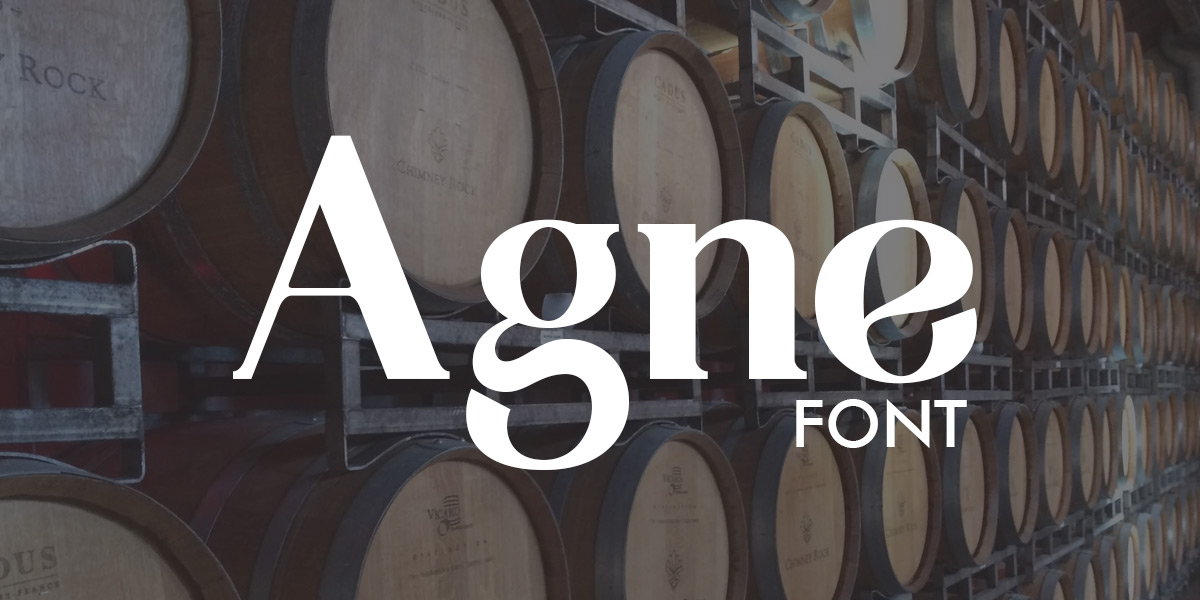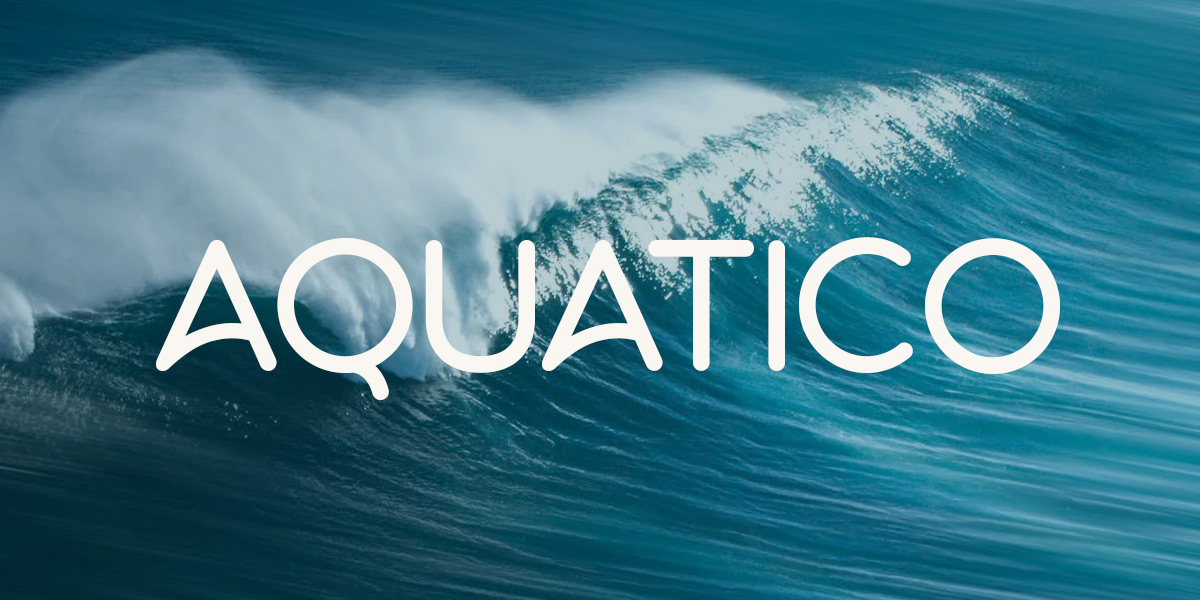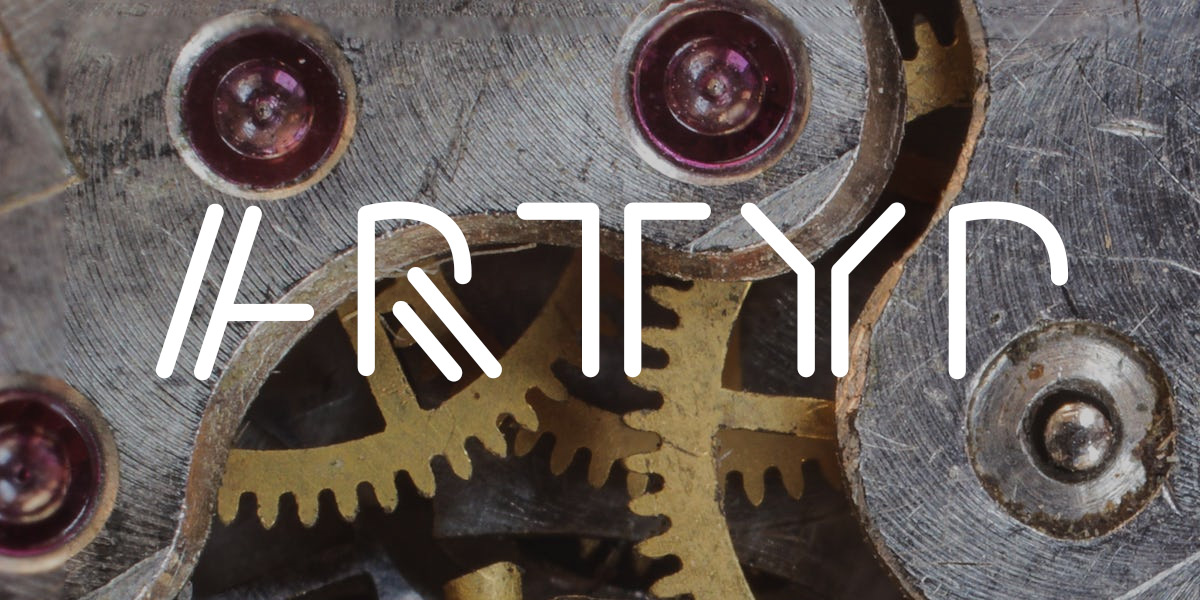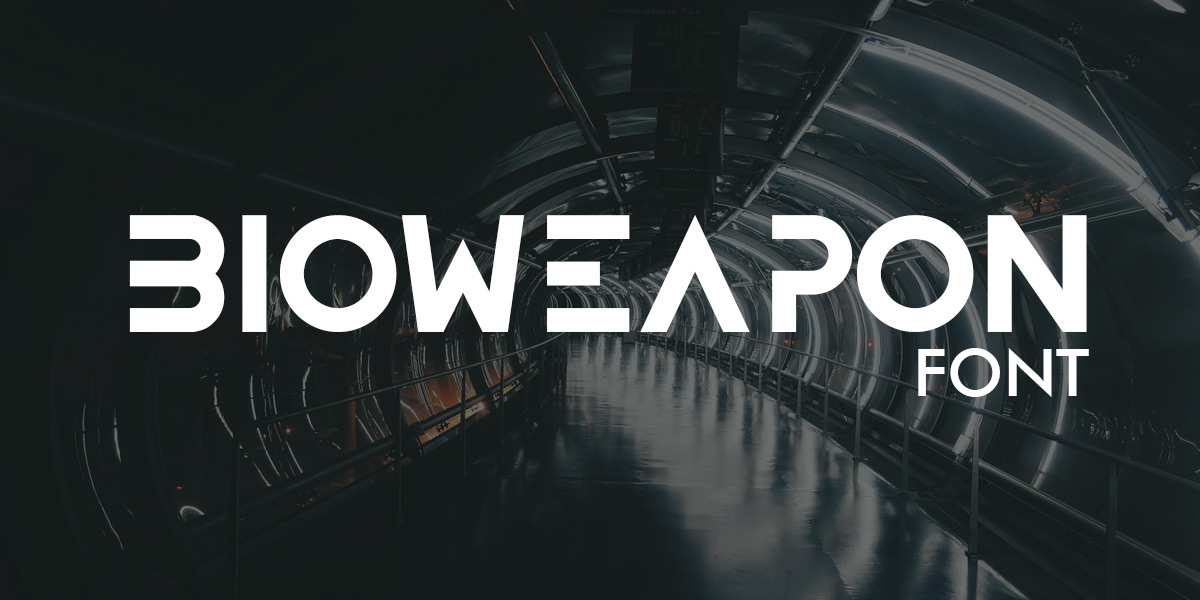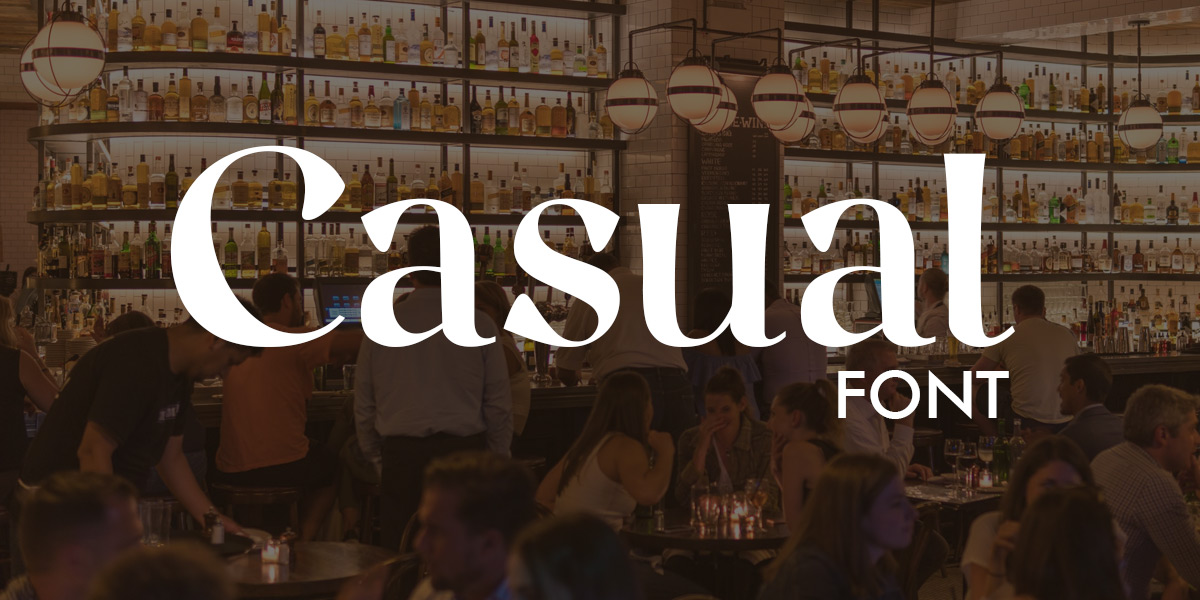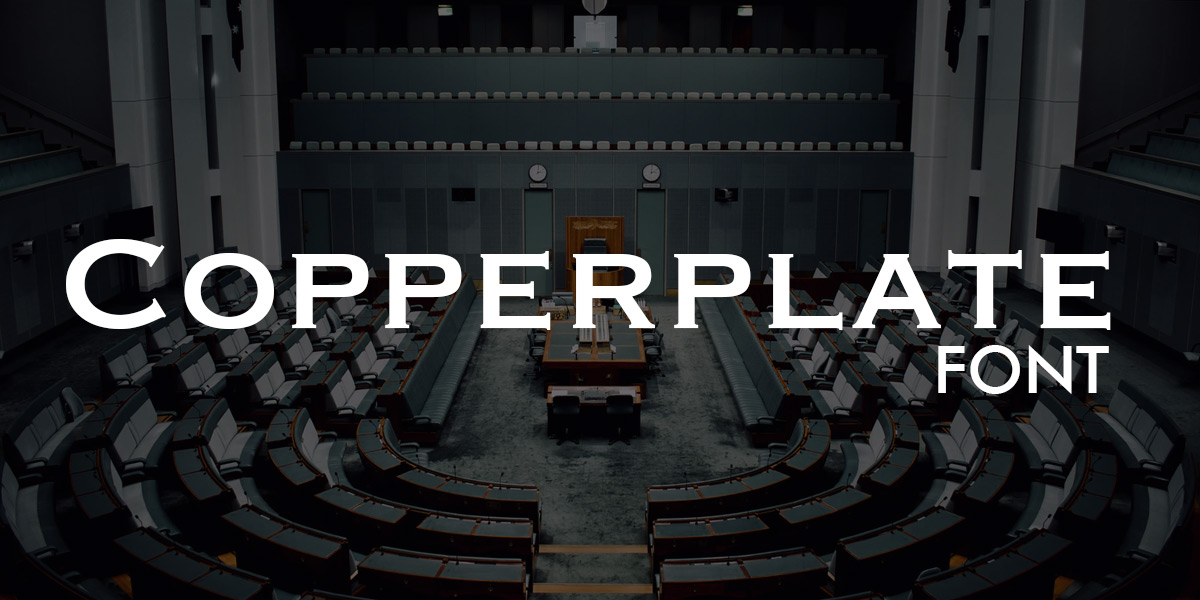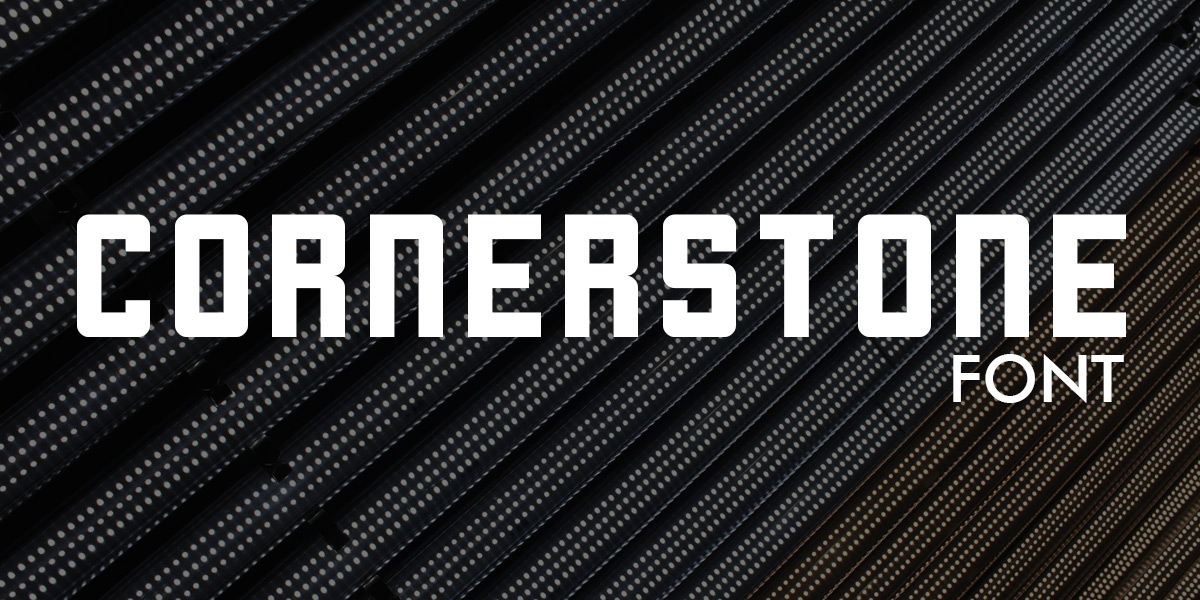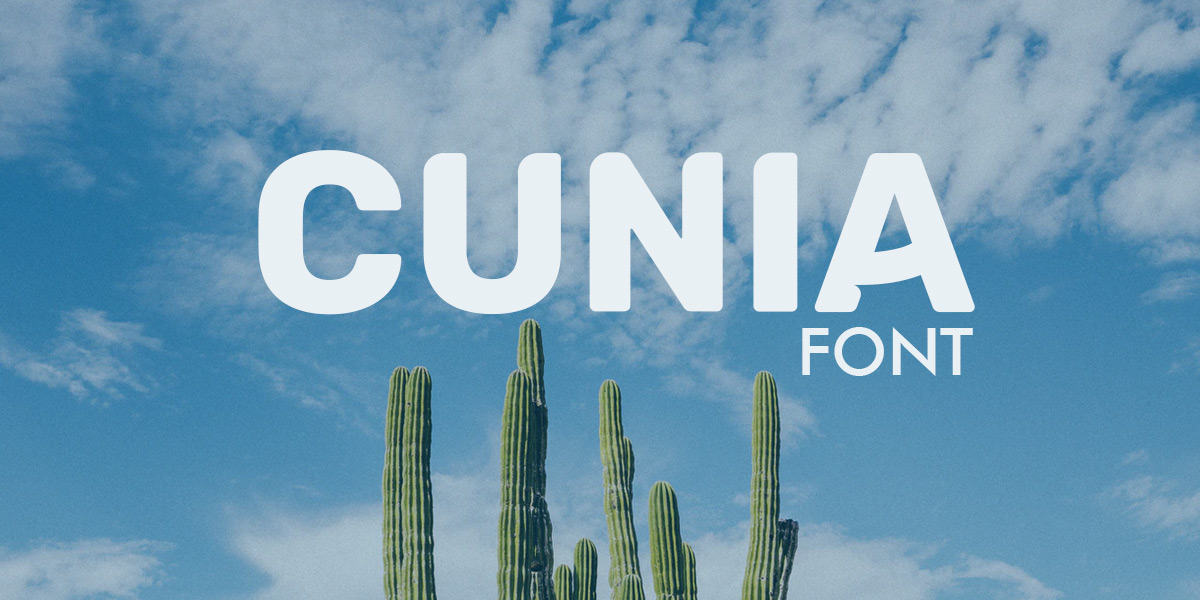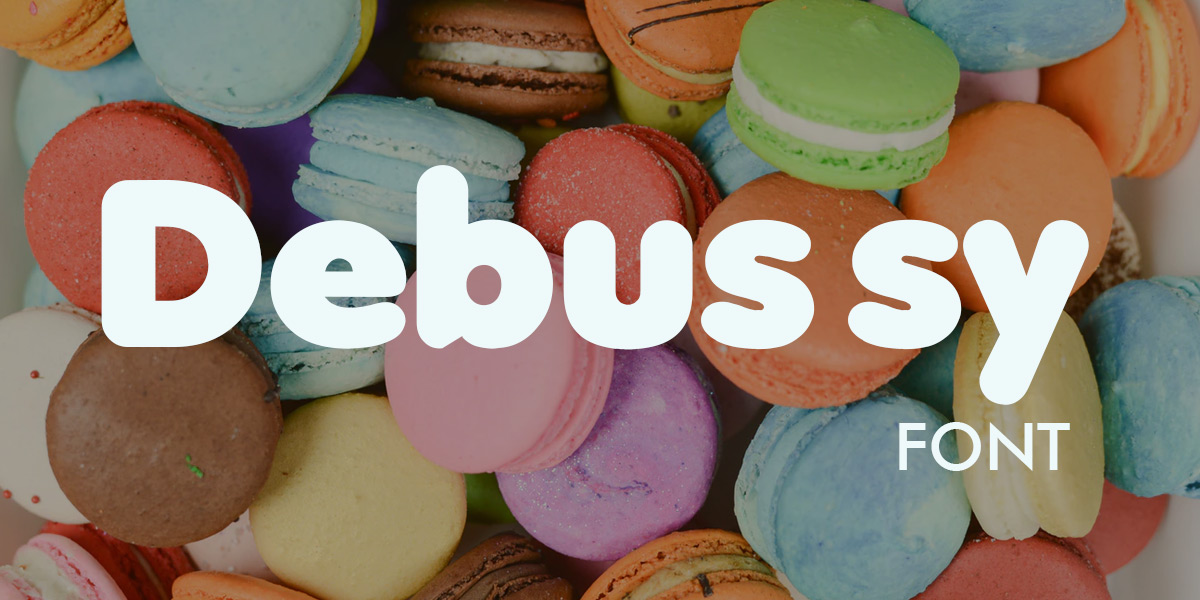
I 30 migliori font per un logo fantastico
30 migliori font per progettare un fantastico
Quando cerchiamo il giusto font per il nostro logo, ci ritroviamo di fronte a una quantità di opzioni che può essere sovrastante. Il modo più veloce per snellire la ricerca e trovare il font perfetto è iniziare la ricerca avendo in mente che tipo di font meglio si addice al nostro brand.
Scegliere il font giusto per un logo
Il font giusto per un logo non è una questione di preferenze personali. Il vostro logo deve abbinarsi al vostro brand. Per fortuna, trovare il font giusto per il vostro brand è più una scienza che un’arte, ed ecco alcune formulette che potrebbero tornarvi utili:
formale e sofisticato = font con grazie
casual = font senza grazie
audace e volto all’azione = font audaci
casalingo e organico = font calligrafici
moderno e avanzato = font futuristici
strambo e simpatico = font creativo
Quindi, prima di scegliere un font, bisogna avere una comprensione cristallina del proprio brand. Siete una startup audace che vuole sconvolgere l’intera industria, o un fornitore di servizi vecchia scuola che è orgoglioso di mantenere vivi i valori tradizionali? Se avete bisogno di aiuto per capire il vostro brand e come funziona un font nell’ambito del branding, date un’occhiata al nostro articolo sulle varie famiglie di font.
Eccovi cinque esempi dei nostri diversi font da ognuna delle nostre sei categorie.
Arrotondati
I font arrotondati sono un’ottima scelta per ogni brand che vuole essere facilmente accessibile. Un font può essere arrotondato in molti modi, ad esempio:
Klasik
Font Logogenia classica
Klasik è un font tutto maiuscolo e non convenzionale. Una delle cose che lo fanno spiccare è che i bordi delle lettere non sono delle linee dritte perfette; hanno una qualità calligrafia, malleabile che fa sì che le lettere sembrino scolpite nell’impasto. È un font perfetto per i fornai, gli scultori e qualsiasi compagnia che presenta i propri prodotti come fatti a mano.
Fontastique
Fontastique Logogenie
Fontastique va al di là di ciò che ci aspetteremmo di solito da un font sans serif, con le sue lettere che sono quasi dei cerchi completi. Per esempio, guardate la D minuscola. Essendo un font formoso con pochissimi angoli taglienti, Fontastique dona una sensazione morbida, femminile che lo rende perfetto per qualsiasi prodotto di bellezza rivolto alle donne.
Orborn
Font Orborn Logogenia
Così come gli altri font arrotondati, anche Orborn trasforma certe lettere (come la A minuscola) in dei cerchi perfetti. Una delle cose più belle di Orbon è che trasforma alcune delle lettere maiuscole in delle versioni più grandi delle lettere minuscole, rendendolo così ancora più amichevole e facendo di questo font un ottimo font per qualsiasi brand che vuole essere l’anima della festa.
Maxwell
Carattere Maxwell Logogeny
Maxwell è un font con linee dritte, angoli arrotondati e qualche stranezza. Guardate l’H maiuscola e l’altezza della minuscola corrispondente. A una prima occhiata, è un font dall’aspetto pulito e convenzionale, ma se ci soffermiamo un attimo, ecco che possiamo ammirare tutta la sua personalità. Maxwell è un’ottima scelta per un brand con una personalità simile: ammodo, ma con un sottotono piuttosto bizzarro.
Aquatico
Font Aquatico Logogenie
Come implica il nome, Aquatico ha un che di acquatico. Guardate la lettera A e vedrete la cresta di un’onda nella linea di mezzo. Non è l’unico punto in cui questo font è libero e aperto come l’oceano. Certe lettere maiuscole, come la K e la R, hanno delle sezioni staccate (dateci un’occhiata nel nostro creatore di loghi per capire cosa vogliamo dire) che donano una sensazione di qualcosa rilassato, all’aria aperta.
Creativo
Come potete probabilmente immaginare, la nostra collezione di font creativi è la più variegata. Sono font per brand che non rientrano in canoni convenzionali.
Inzomniak
Font Inzomniac Logogenie
Inzomniak è un font che sembra scarabocchiato con un pennarello. Se volete che il vostro testo assomigli a un graffito, Inzomniak è un’ottima scelta. È angolare, tagliente, le lettere sono tutte di dimensioni diversi, e i segni non sono uniformi. Ed è per questo che funziona. Non è rifinito né vuole esserlo, il che lo rende perfetto per quei brand che vogliono comunicare la stessa cosa riguardo sé stessi.